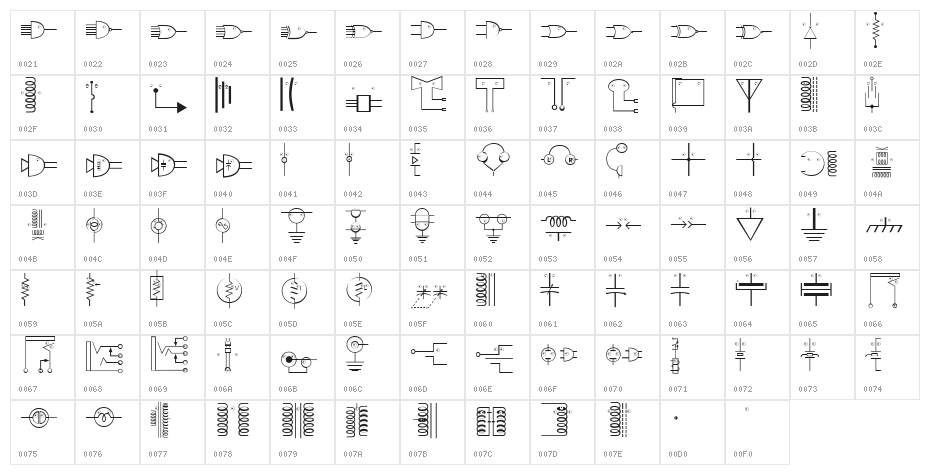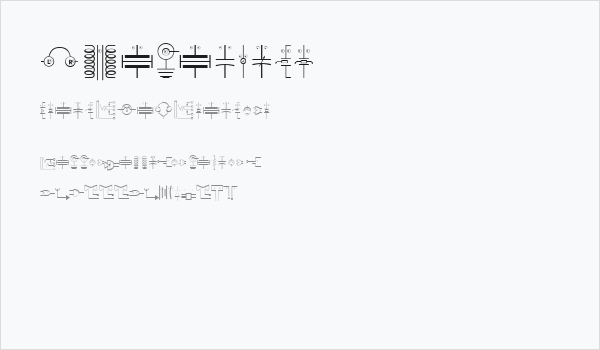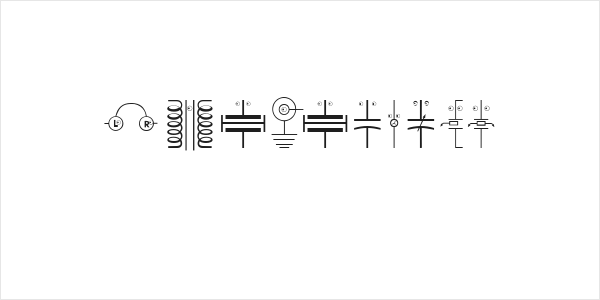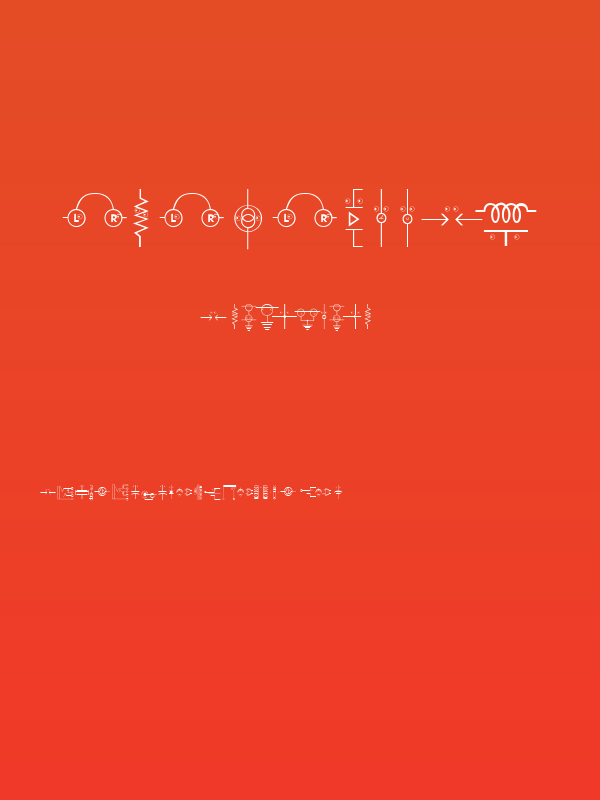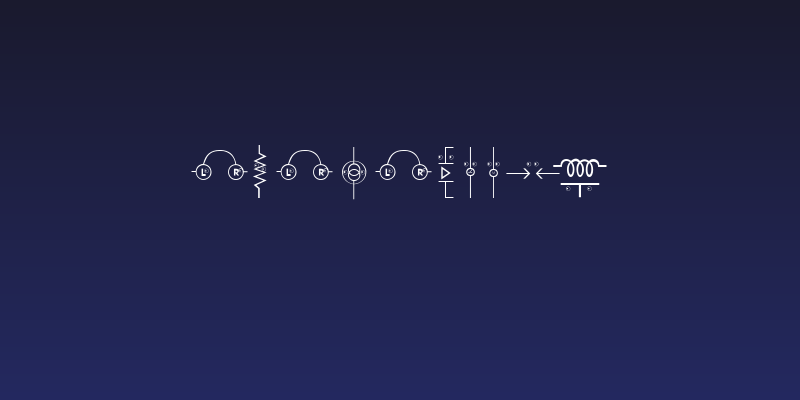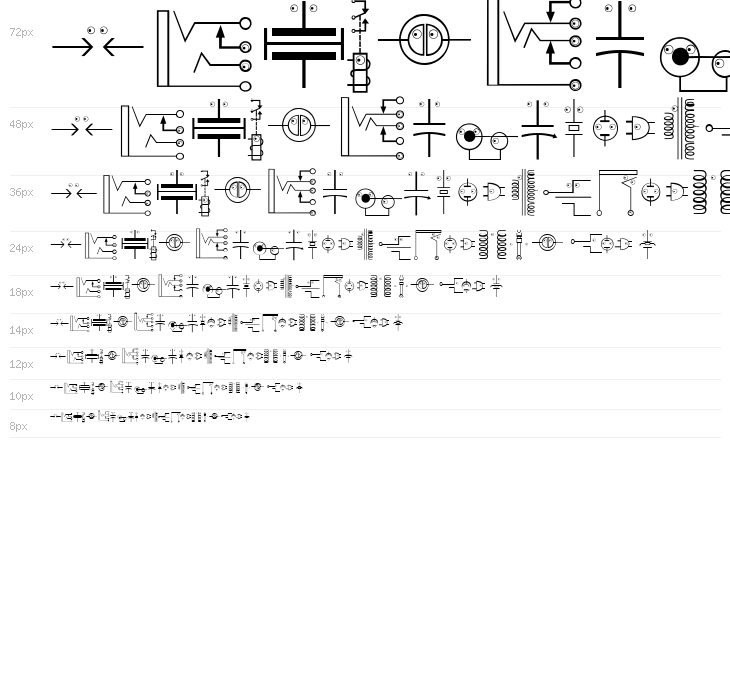
EyelecBats Font
| Stile generale | Technical, Schematic |
| Caso d'uso | Decorative, Technical illustrations |
| Progetti proposti | Ideal for educational materials in electronics, technical illustrations, engineering presentations, and themed graphic designs. |